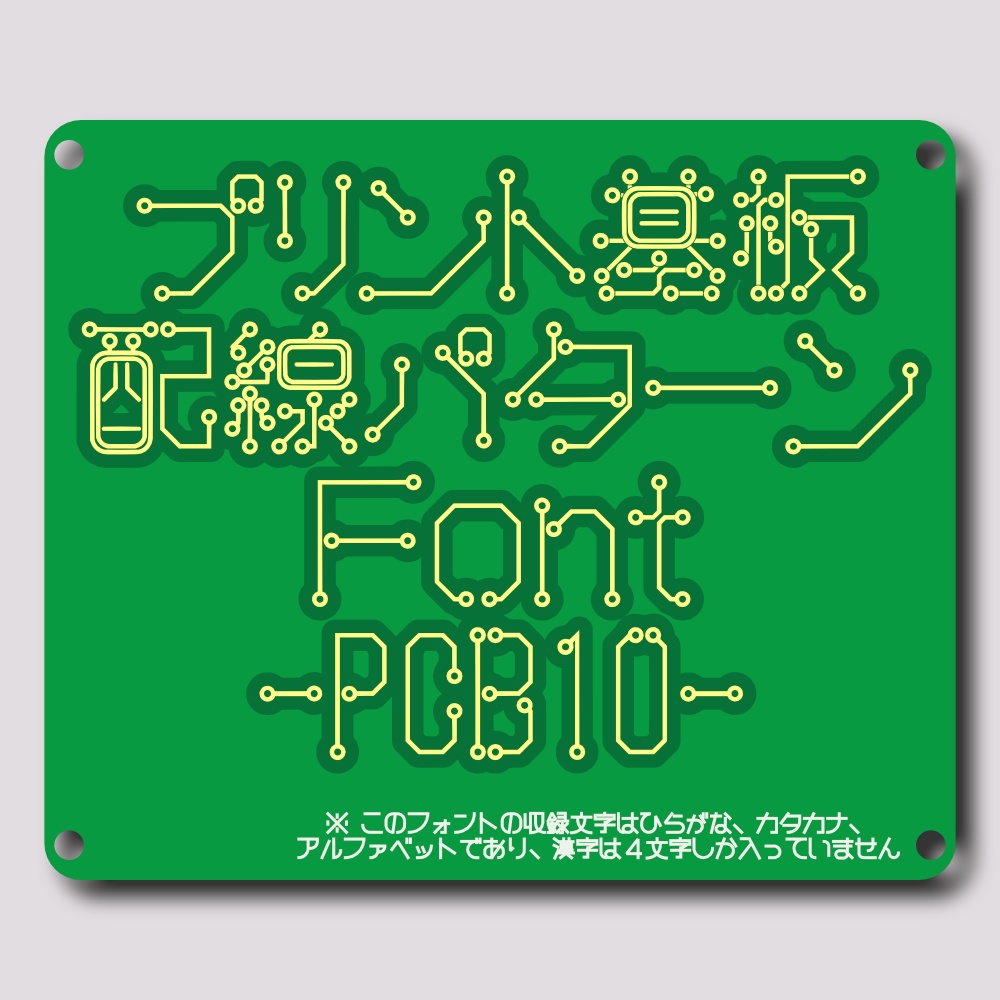
フォント PCB10 プリント基板配線パターンフォント
プリント基板の配線パターンをイメージしたフォントです。
文字の収録範囲
半角(固定幅):英数字記号(基本ラテン文字)、カタカナ 全角(可変幅):英数字記号、ひらがな、カタカナ、漢字(基板配線) スペース含め、計436グリフ
余談
このフォントはグリフの線密度が高い方が見栄えが良いので、評判が良ければ漢字を収録したいところ。 その場合、教育漢字~JIS第1水準まで(「鬱」等の複雑な漢字はパス)とし、有料フォントになると思いますが。